5 Aplikasi Font Generator agar Feed Instagram Makin Estetik
Estetika akun Instagram memang penting bagi sebagian besar pengguna, apalagi bagi mereka yang dikenal sebagai selebgram. Sebab, tampilan akun yang menarik akan mendatangkan banyak likes dan pengikut baru.
Berbagai cara bisa dilakukan agar laman akun tertata rapi dan estetik, seperti menentukan tema, mengunggah foto dengan warna senada, hingga menggunakan filter khusus. Selain itu, foto yang diunggah sebaiknya juga didukung dengan tampilan caption yang tidak kalah menarik pula.
Kamu bisa menggunakan aplikasi font generator yang mempunyai banyak pilihan jenis huruf dan emotikon untuk caption Instagram. Berikut ini lima rekomendasi aplikasi font generator untuk smartphone Android agar tampilan Instagram kamu makin estetik!
1. Fontify
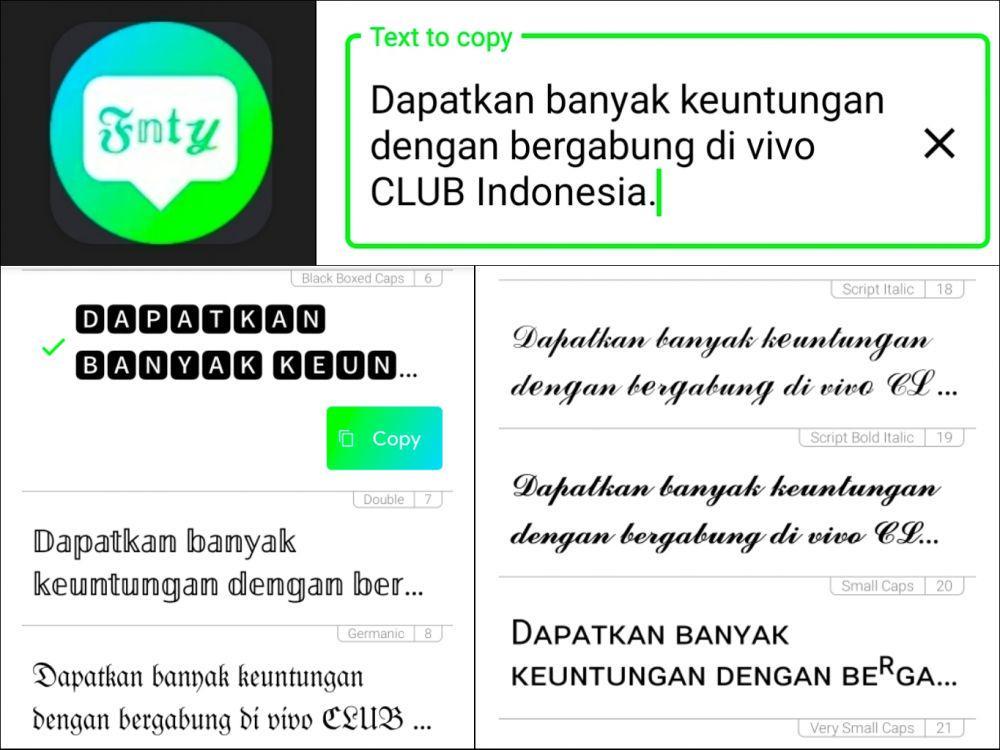
aplikasi Fontify (dok. pribadi/Ratumas Ovvy) Fontify merupakan salah satu aplikasi fon Instagram yang populer untuk Android. Terbukti, aplikasi ini telah diunduh sebanyak lebih dari 1 juta kali dan mendapat nilai 4,5/5. Nilai yang nyaris sempurna, kan?
Bukan hanya memberikan banyak jenis pilihan fon yang unik, Fontify juga didesain untuk memudahkan kerja pengguna. Kamu tinggal mengetik teks, memilih jenis fon yang kamu inginkan, lalu memencet tombol salin yang ada di sebelahnya.
Uniknya lagi, Fontify memiliki pintasan langsung ke Instagram. Tidak cukup sampai di situ, fon yang disediakannya juga bisa digunakan di WhatsApp dan Facebook, lho.
2. I Fonts
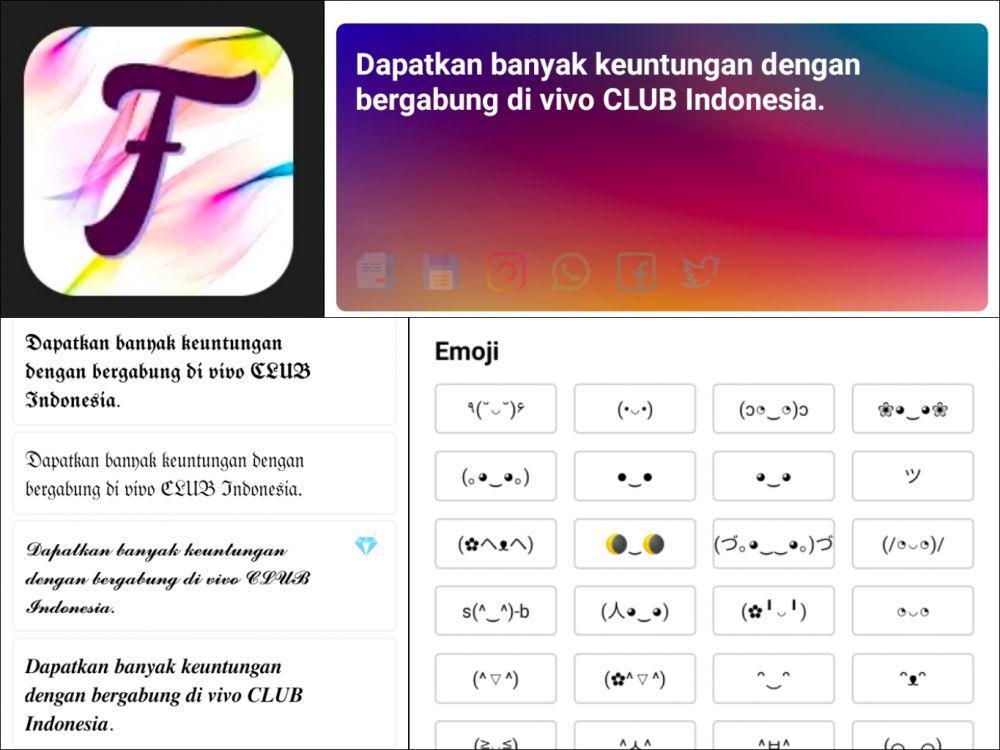
aplikasi I Fonts (dok. pribadi/Ratumas Ovvy) I Fonts memang tidak sepopuler Fontify. Aplikasi keluaran Segrok Kroto ini telah diunduh 100 ribu kali dan mendapat nilai 4,3/5. Namun, aktivitasmu di media sosial akan sangat terbantu bila menggunakannya.
I Fonts memiliki sekitar 27 jenis pilihan huruf yang indah, mewah dan estetik. Selain itu, ada pula pilihan ratusan emotikon yang membuat tulisan menjadi semakin menarik.
Siapa pun tidak perlu bingung menggunakannya karena I Fonts sangat mudah dipahami. Aplikasi ini mempunyai pintasan ke Instagram, Facebook, WhatsApp dan Twitter. Bahkan, kamu juga bisa membuat konten Instagram Stories langsung dari sini. Keren banget, kan?
3. Fonts for Instagram
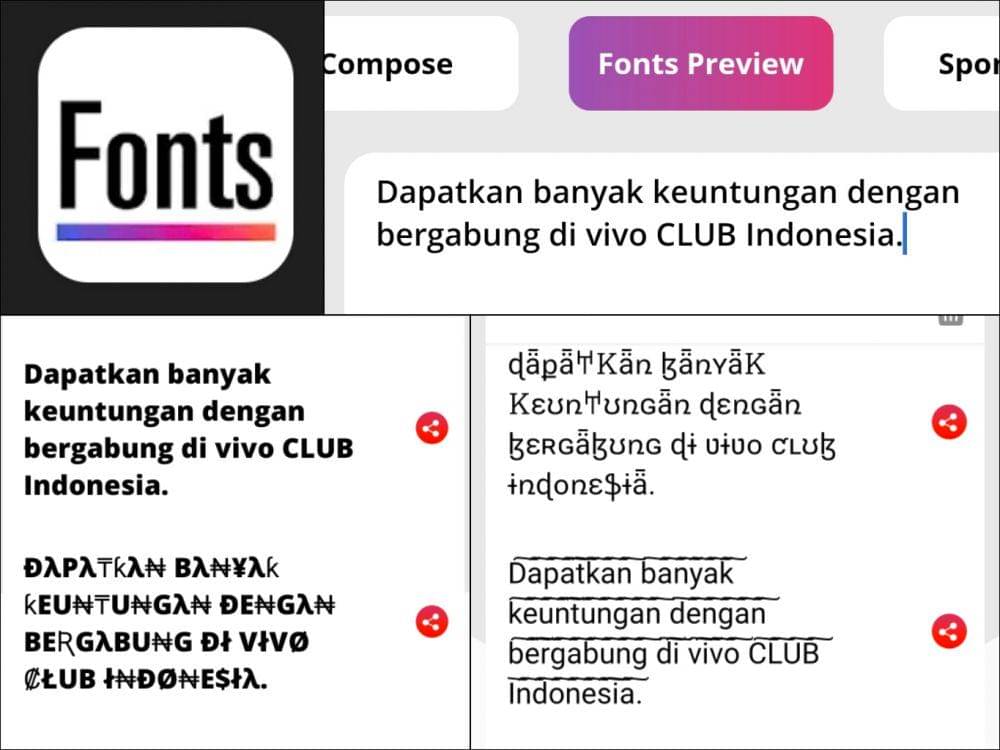
aplikasi Fonts for Instagram (dok. pribadi/Ratumas Ovvy) Fonts for Instagram telah diunduh lebih dari 5 juta kali dan mendapat nilai 4,4/5. Apakah kamu salah satu penggunanya? Aplikasi milik Pixster Studio ini memang memiliki berbagai fitur yang memudahkan kerja pengguna Android.
Kamu bisa menyesuaikan caption dan bio Instagram sesuka hati dengan ratusan pilihan fon dan emotikon yang tersedia. Beberapa fon memang mengharuskan pengguna membeli paket berbayar. Namun, tenang saja karena kamu bisa mendapatkannya secara gratis dengan menonton video iklan.
Selain itu, Fonts for Instagram juga menyediakan fitur Keyboard Themes untuk membuat tampilan keyboard HP semakin atraktif. Jadi, tidak heran bila aplikasi ini diunduh jutaan orang.
4. Fancy Text
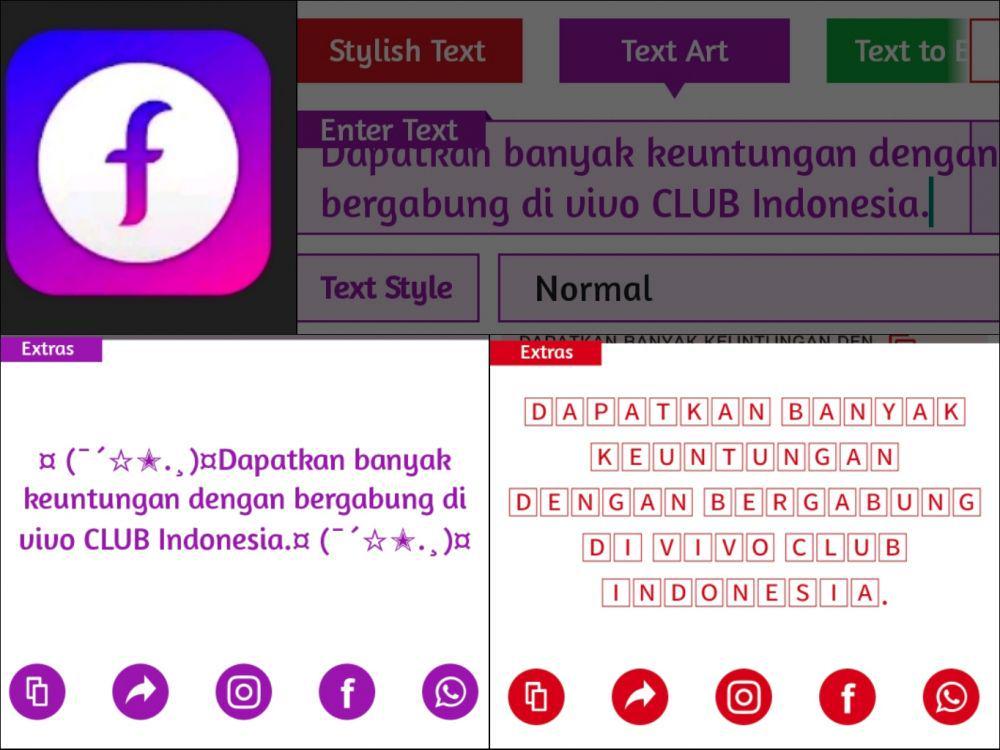
aplikasi Fancy Text (dok. pribadi/Ratumas Ovvy) Kalau kamu sedang mencari ide untuk memperindah bio Instagram, Fancy Text bisa menjadi salah satu aplikasi yang patut dipertimbangkan. Terbukti, 500 ribu pengguna telah mengunduhnya dan memberikan nilai 4,4/5.
Fancy Text menghadirkan banyak pilihan fon yang menitikberatkan pada simbol unik dan lucu. Bahkan, kamu bisa menerjemahkan teks menjadi simbol. Dengan aplikasi ini, bio Instagram kamu akan lebih eye-catching dan berbeda dari yang lain.
Cara menggunakannya juga sangat mudah. Kamu tinggal mengetik, lalu memencet tombol salin yang ada di sebelah pilihan fon. Setelah itu, kamu juga dimudahkan dengan tombol pintasan ke Instagram, Facebook, WhatsApp, atau aplikasi lain yang ada di tombol bagikan.
5. Cool Fonts
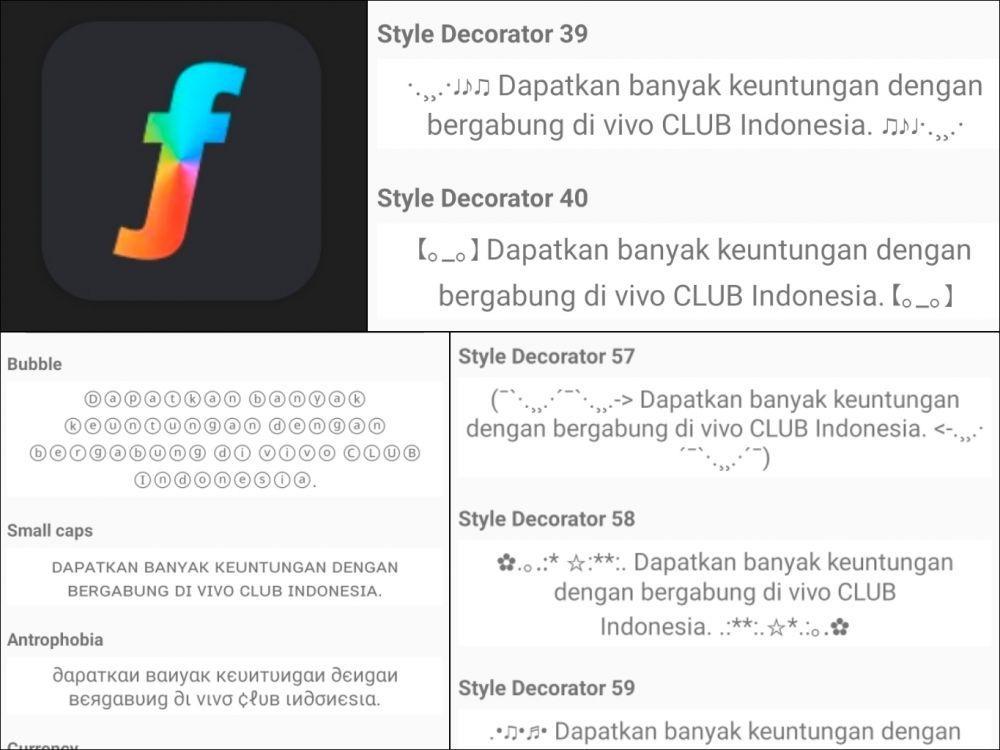
aplikasi Cool Fonts (dok. pribadi/Ratumas Ovvy) Kalau kamu ingin bernostalgia dengan teks dan emotikon lucu yang populer di BlackBerry Messenger (BBM), Cool Fonts adalah aplikasi yang wajib kamu coba. Sudah lebih dari satu juta pengguna mengunduhnya dan memberi nilai 4,3/5 untuk produk Font Keyboard Company ini.
Sayangnya, Cool Fonts belum memungkinkan pengguna untuk langsung mengarah ke aplikasi Instagram dan lainnya. Kamu masih harus menyalinnya secara manual. Namun, ini semua terbayar dengan 70 jenis pilihan fon dan 61 jenis text decorator unik yang dimilikinya.